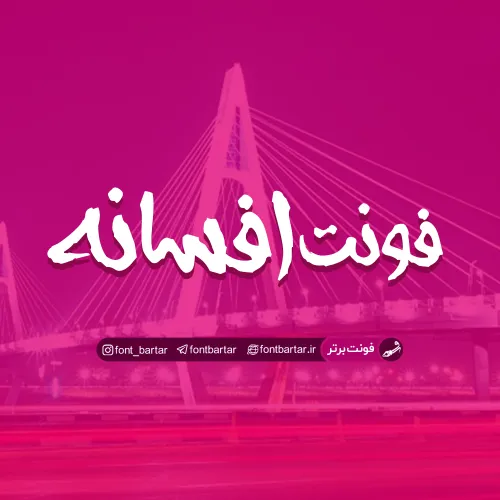
فونت فارسی افسانه
من حسین تقی زاده طراح گرافیک هستم. اخیرا فونتی رو اجرا کردم که خیلی مشتاق هستم اون رو از طریق سایت خوب شما و مراجع دیگه منتشر کنم. فونت افسانه رو چند سال پیش بر اساس استایل دست نوشته و با قلمو و مرکب برای حروف فارسی طراحی کرده بودم. اکنون مفتخرم پس از اجرای کامل، اون رو به عنوان اولین تجربه ام در طراحی فونت در دسترس علاقه مندان قرار بدم.
فونت افسانه مورد استفاده برای:
• طراحان وب سایت و گرافیست های خلاق می توانند از این مجموعه زیبا فونت در طراحی پروژه های تبلیغاتی و تجاری خود کمک بگیرند.